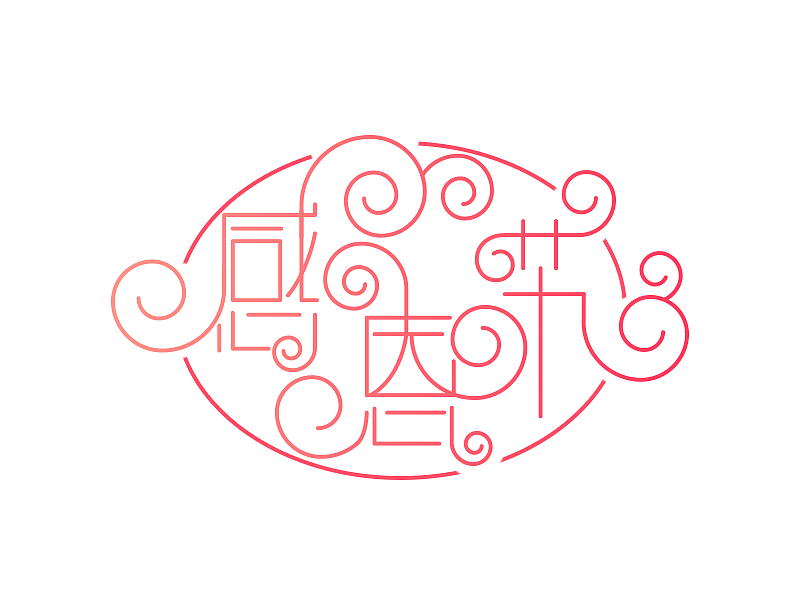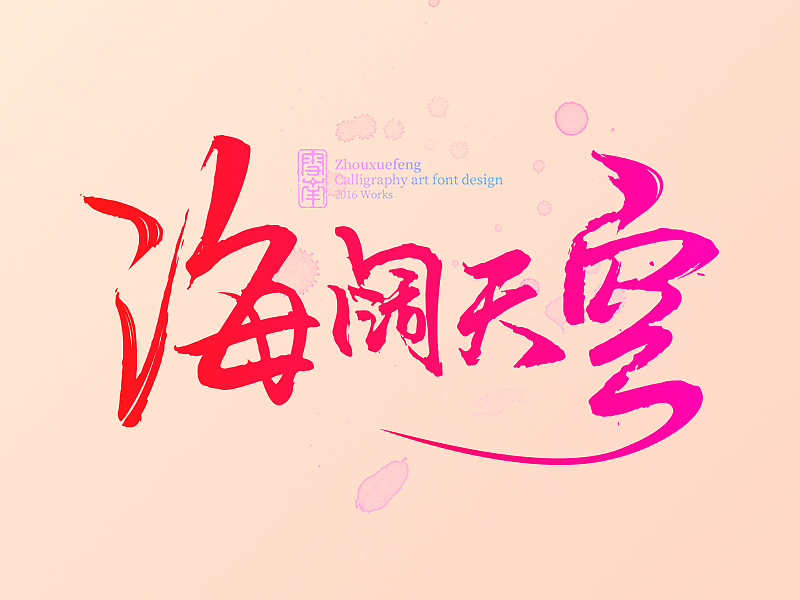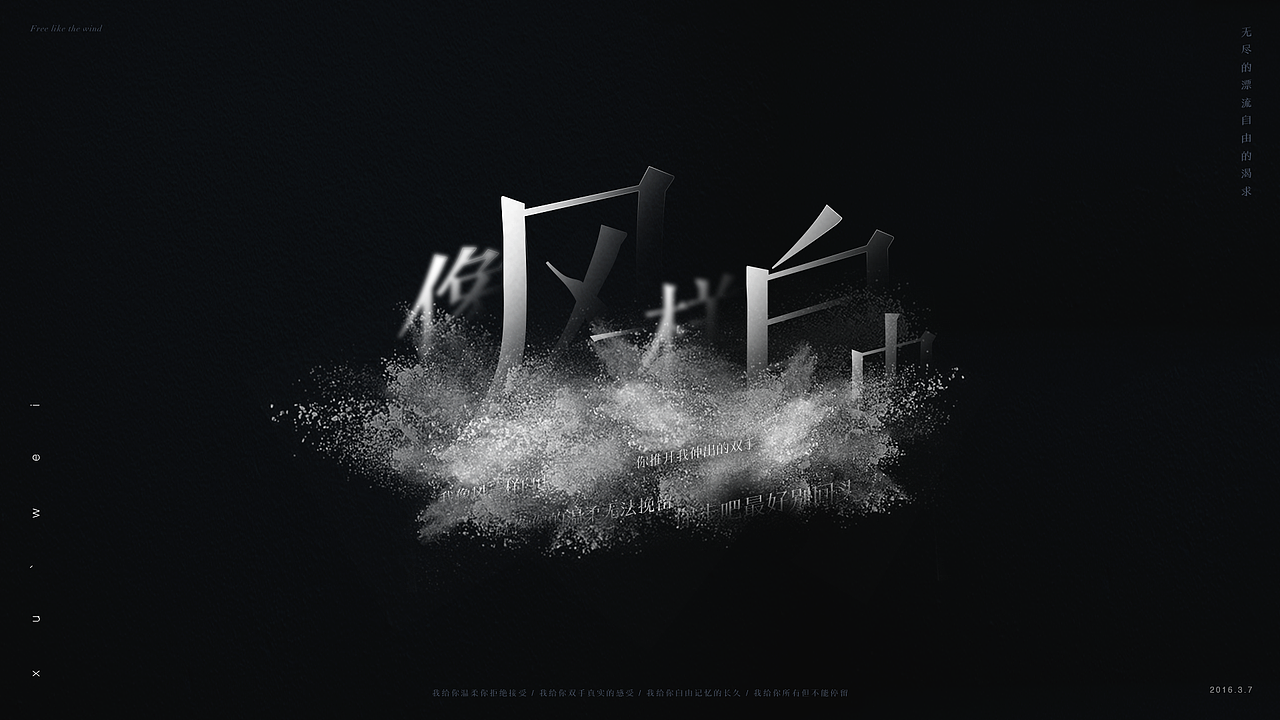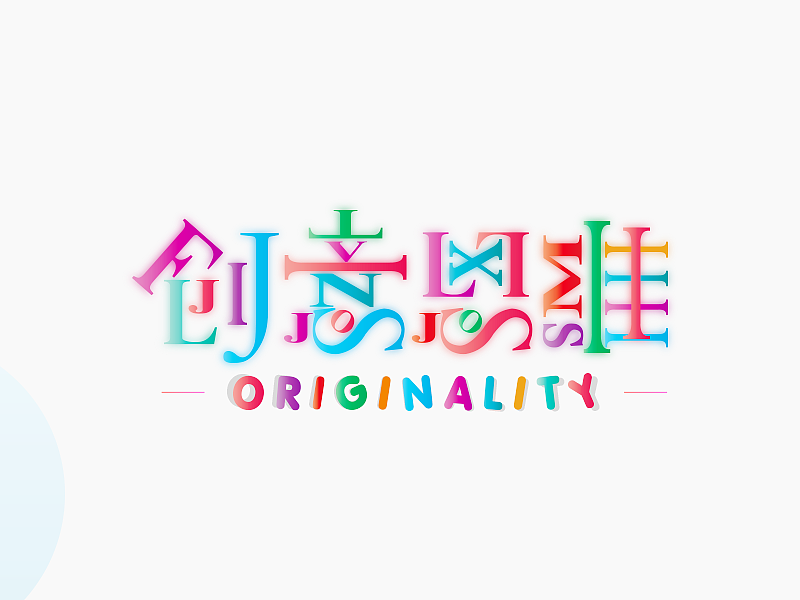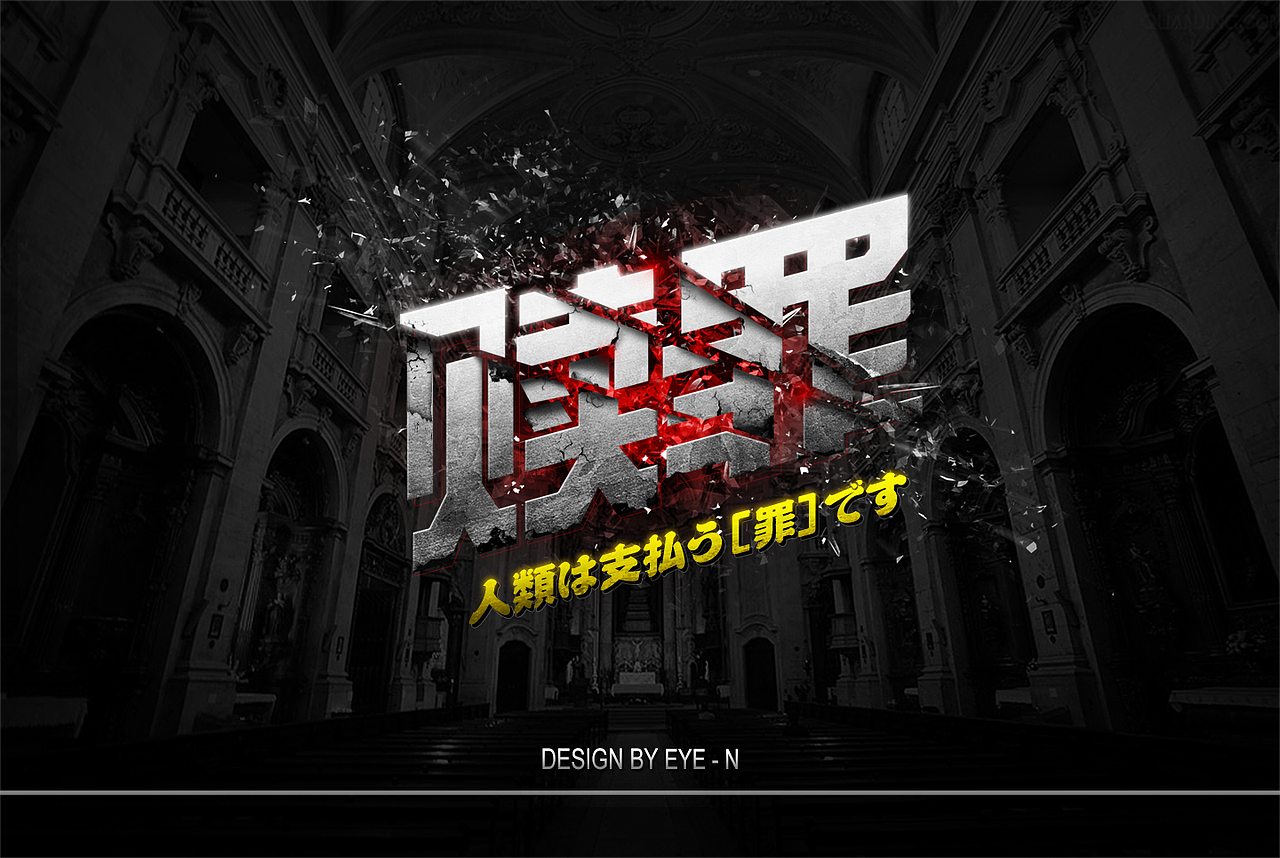
创意字-君临天下
创意字-神出鬼没
SALE字体水溅效果
花纹字-千资丽人
创意字-晓亮
花纹字-爱
花纹字-完美生活
花纹字-中秋快乐
花纹字-感恩节
花纹字-新年快乐
花纹字-星语星愿
创意字-宝贝计划
创意字-创意思维
像风一样自由
创意字-大道致简
创意字-宁静致远
创意字-女汉纸
创意字-闻香识女人
创意字-下午茶
胖胖字-呆萌
胖胖字-猪头三
书法字-顿悟
书法字-海阔天空
书法字-拍案叫绝
书法字-英雄传说
书法字-真善美
书法字-终结战士
月满西楼
字体效果设计
【梦魇】赎罪